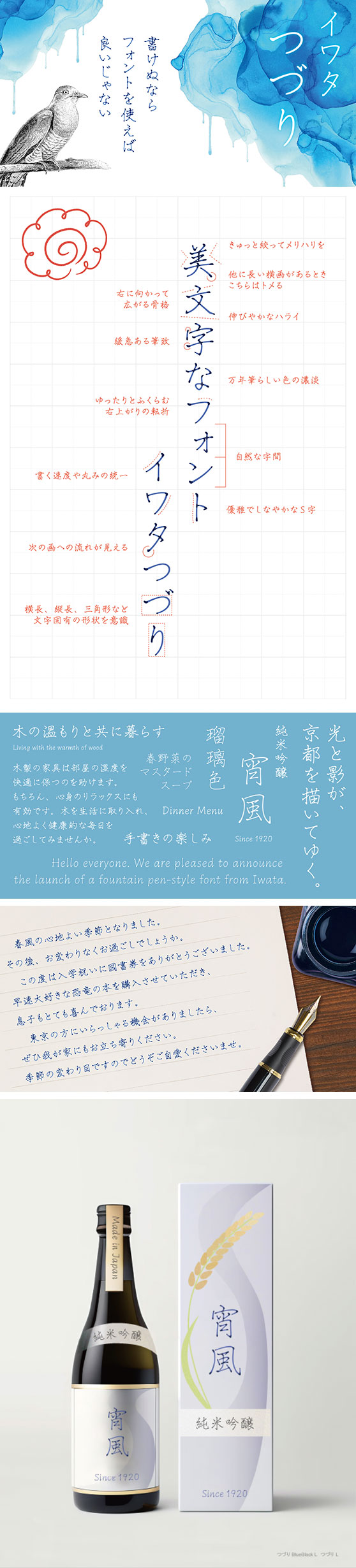
イワタつづり Complete Pack
達筆な人がさらりと万年筆で書いたような、繊細で美しい万年筆風フォント。丁寧な挨拶状からカジュアルなメッセージまで、さまざまなシーンにお使いいただけます。
Complete Packには、通常の単品アウトラインフォント(Lウェイト・Rウェイト)に加え、万年筆のインクの濃淡を表現した「BlueBlack」「Sepia」「White」の3種類の色のカラーフォントも収録。DTPソフトなどを用い、通常のアウトラインフォントに「Layer」を重ねることで、お好みのインク色を表現することもできます。